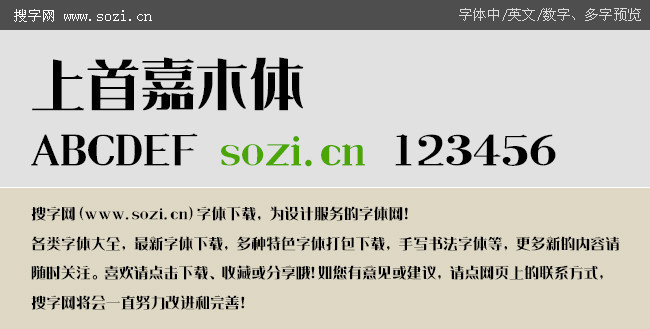
上首嘉木體
搜字網(wǎng)給大家提供一款上首嘉木體中文字體下載,上首嘉木體是一款中文藝術(shù)字體,字形修長(zhǎng)方正,特點(diǎn)處做圓角處理,使其簡(jiǎn)潔規(guī)范,卻又剛中帶柔,別有新意。適用于搭配標(biāo)志、廣告標(biāo)語(yǔ)、商業(yè)廣告等廣告設(shè)計(jì)。